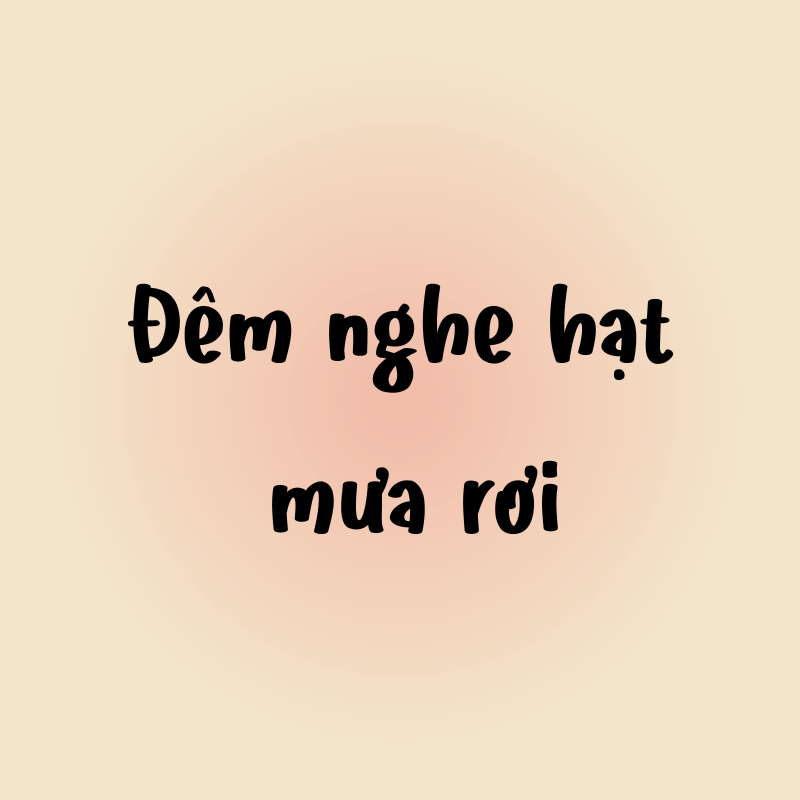
Font Việt hóa , font BrightNight
Font Việt hóa font BrightNight – Phong Cách Hiện Đại, Đẹp Mắt
Font VN BrightNight là bộ font Việt hóa độc đáo, được thiết kế với phong cách hiện đại, sắc nét, phù hợp cho nhiều dự án sáng tạo. Với kiểu chữ thanh lịch, đường nét cân đối, font này thích hợp cho thiết kế đồ họa, trình bày văn bản, logo, banner và các ấn phẩm truyền thông.
Đặc điểm nổi bật của font BrightNight :
• Hỗ trợ đầy đủ Tiếng Việt, bao gồm các ký tự có dấu, đảm bảo tính thẩm mỹ và dễ đọc.
• Đa dạng kiểu chữ (regular, bold, italic…) giúp thiết kế linh hoạt, phù hợp nhiều phong cách.